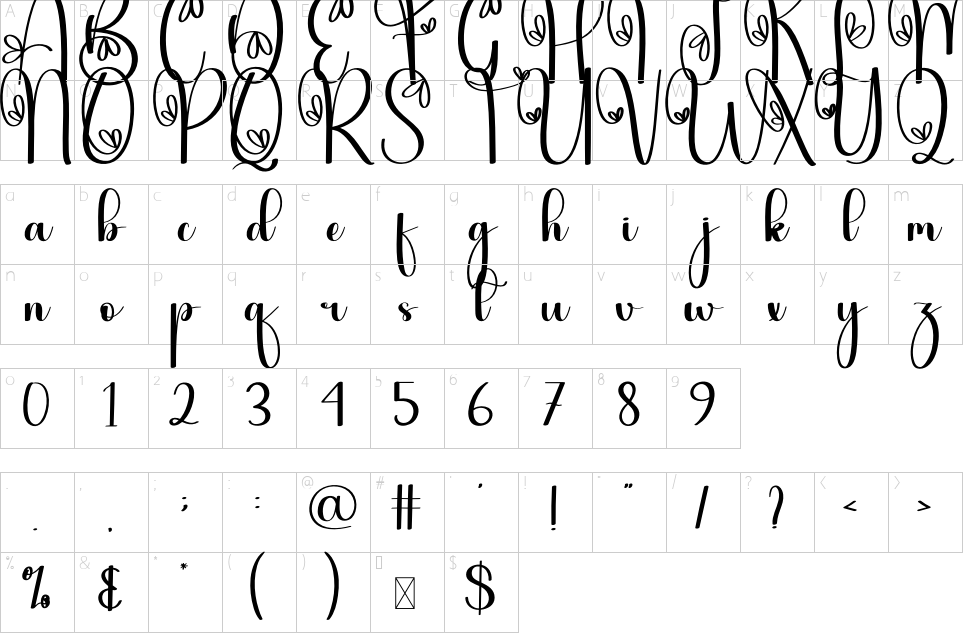
Agora está disponível para download uma fonte extremamente enriquecedora para o seu design gráfico, especialmente adequada para projetos criativos e coloridos. Trata-se da fonte “Monkey”, um design moderno e atraente criado pelo talentoso designer william jhordy. Esta fonte, semelhante às letras de animais exuberantes, pode adicionar um toque de brasilidade e energia a qualquer projeto, seja um design de aplicativos, site, logo, ou até mesmo uma publicação no Instagram. “Monkey Font | 1001 Free Fonts” é uma fonte gratuita para Windows e Mac, disponível para quem procura personalidade e diversão em seu design. Como parte da nossa vasta coleção de 1001 Free Fonts, este é mais um passo em direção ao seu design mais criativo e divertido.